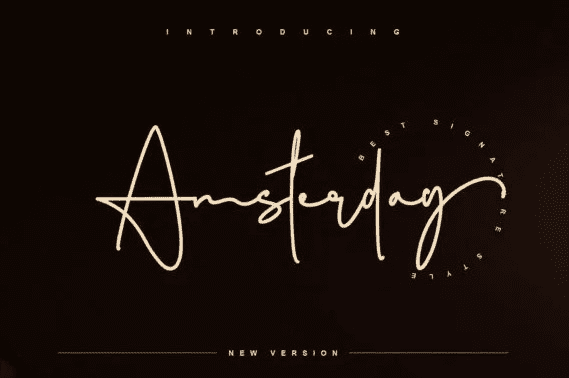
Amsterday - это красивый шрифт сценария.
Этот шрифт был тщательно разработан, чтобы воссоздать естественный рукописный текст,и он имеет милые штрихи.